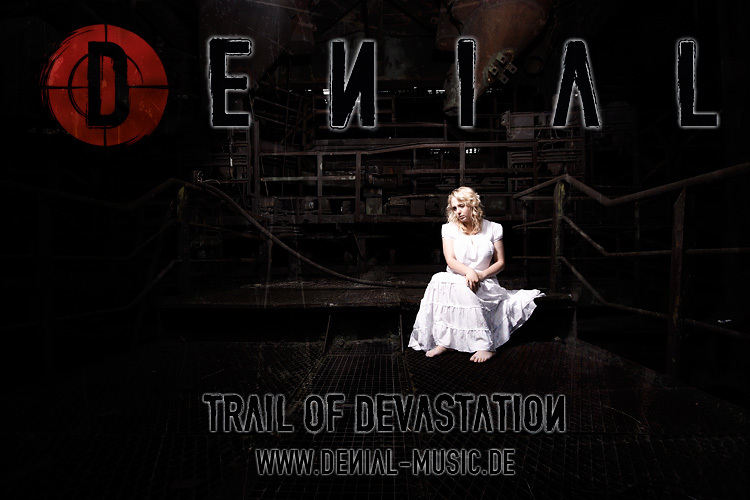
Denial, firmato Patrick Dehen Grafik-Design, è un font display gratuito in maiuscolo dallo stile eroso, dotato della forza di una tipografia industriale usurata. Lettere alte e pesanti presentano bordi scheggiati, superfici graffiate e un'usura irregolare, creando la cruda impressione di una stampa tipografica senza perdere la forza delle loro silhouette decise.
Questa atmosfera abrasiva e fotocopiata conferisce al font gratuito una collocazione naturale su poster punk, copertine di album, branding streetwear, grafica di protesta e copertine editoriali dal taglio graffiante. La sua consistenza vissuta si sposa perfettamente con la fotografia, il collage o le forme grafiche piatte, dando voce a un tono ribelle che profuma di inchiostro, carta stampata e materia vissuta, ben lontano dalla perfezione digitale.